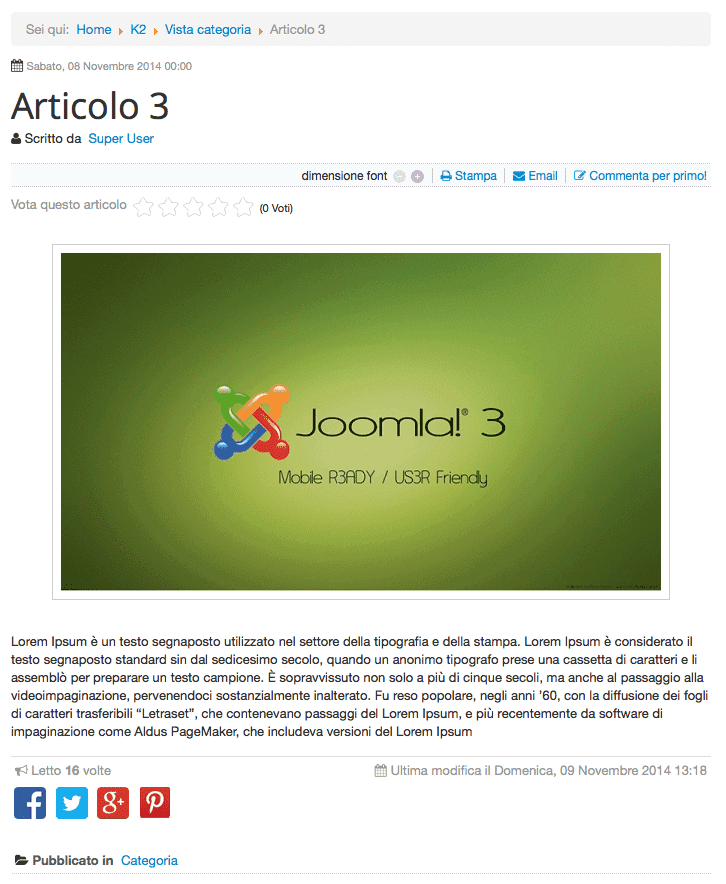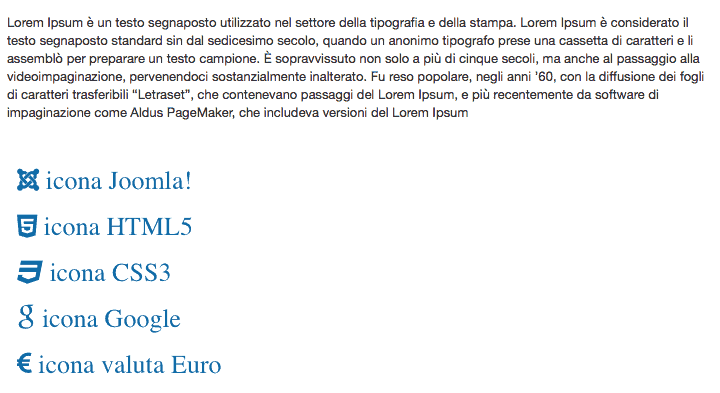
NS FontAwesome è un plugin gratuito che introduce l’utilizzo del font web “Font Awesome”. Questo tipo di font permette di utilizzare delle icone vettoriali sul proprio sito internet (in gergo glyph icons), senza avere la necessità di crearle ogni volta con qualche software vettoriale.
Con questo font possiamo davvero sbizzarrirci per personalizzare il nostro sito Joomla!, vediamo come fare e vediamo anche qualche idea 🙂
Come inserire glyph icon su un sito Joomla!
Le glyph icons si inseriscono attraverso un tag HTML denominato “i” (ossia icon), all’interno del tag viene specificata la classe che richiama, in questo caso, l’icona di Font Awesome, analizziamo il codice :
il codice è composto da una parte variabile ed una costante
Parte costante : <i class=”fa fa-joomla“></i>
La costante viene utilizzata per richiamare il font ed ovviamente il tag
Parte variabile : <i class=”fa fa-joomla“></i>
La parte variabile invece identifica il tipo di icona da inserire, in questo caso mostra l’icona di Joomla!
Come inserire icone glyph icon all’interno di un articolo Joomla!
Per inserire una o più icone di Font Awesome all’interno di un qualunque articolo o modulo Joomla! è molto semplice.
- Aprire un articolo / modulo in cui vogliamo inserire la glyph icon
- Importante ! Disabilitare o utilizzare la funzione di inserimento HTML puro del nostro editor . Questo è molto importante perché se inseriamo puro codice HTML nell’ editor WYSISWG Joomla!, verrà interpretato come testo normale, quindi a front end non vedremo la nostra icona glyph.
- Fatto ciò, identifichiamo quale icone vogliamo inserire e scriviamone il codice HTML all’interno dell’editor, esempio :
12345<i class="fa fa-joomla"></i><i class="fa fa-html5"></i><i class="fa fa-css3"></i><i class="fa fa-google"></i><i class="fa fa-eur"></i> - Il risultato sarà una cosa simile (ho aggiunto un po’ di CSS per spaziarle ed ingrandirle altrimenti erano piccoline e non rendevano l’idea). Il testo l’ho aggiunto io
Come ridimensionare le icone di Font Awesome
Nel caso voleste ingrandire le icone secondo le vostre esigenze, potete agire in diversi modi, ne cito un paio
Il secondo metodo invece è quello di scrivere il CSS inline e modificare la dimensione solo delle icone che ci interessano.
Esempio
Da
A
in questo modo andremo a “colpire” la singola icona.
Esempio di utilizzo di Font Awesome nel template di K2